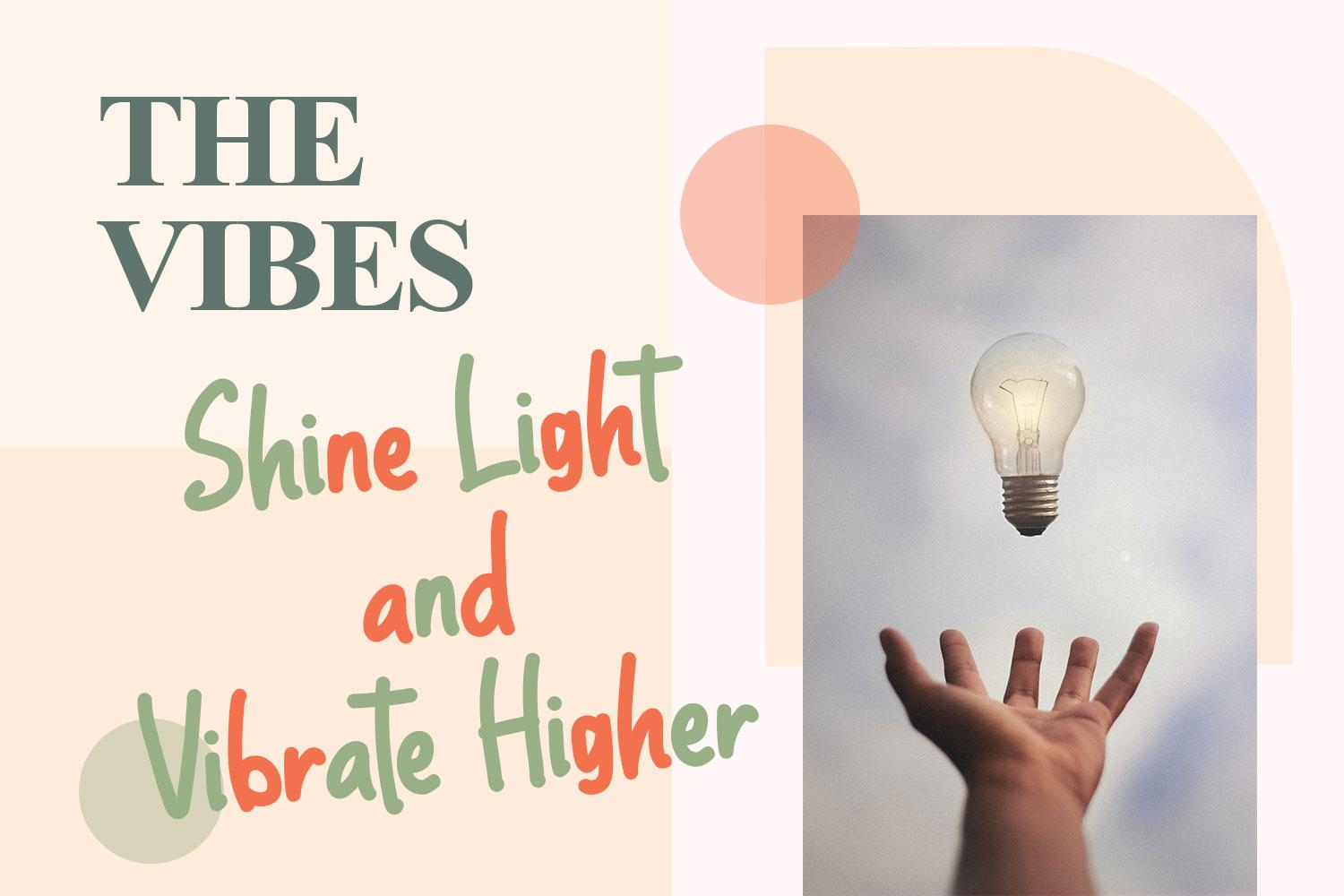
BasileyCafont是一款充满活力、快乐且富有魅力的娱乐性展示工具。这款工具适用于各种矢量设计、印刷品,如数码婚礼、博客、网上商店、社交媒体等,而印刷品可用于现场的产品服装、配饰、包、别针、徽标、名片、水印等。BasileyCafont是一款充满活力的娱乐性展示工具,祝您愉快并愉快。此字体适用于各种矢量设计、打印,如数字婚礼、博客、在线商店、社交媒体,而打印可用于产品服装、配件、包、别针、徽标、名片、水印和其他许多领域。